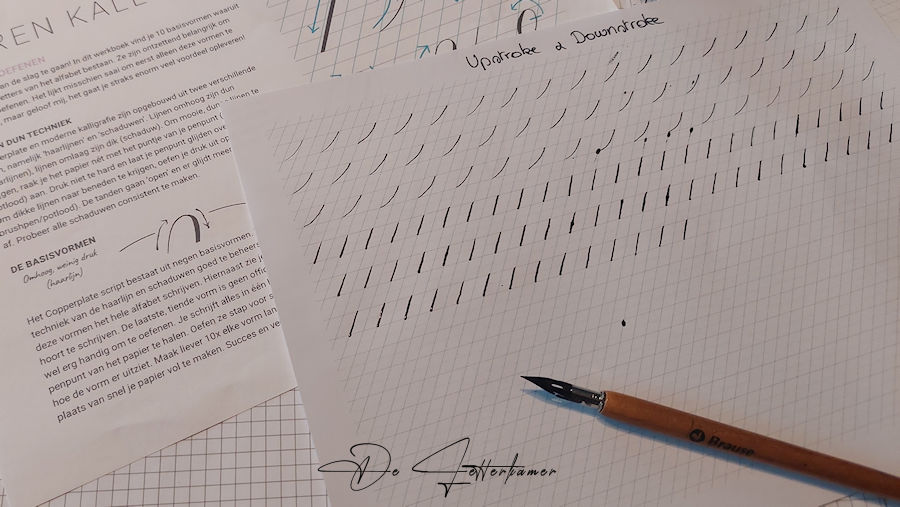
Zo, zoals beloofd de reis gaat verder, en daarover vertel ik meer. Ik ben begonnen met de meeste eenvoudige basisvormen: namelijk de upstroke en de downstroke. De upstroke is meer glijden met de pen over je papier, de downstroke daar zet je meer druk op de pen. De lijnen moeten ook mooi glad zijn ook niet hobbelig. En daar ga ik nog steeds de mist in.
Dit was de 1ste keer en meteen een uitschuiver gemaakt, vlekken gemaakt.
Dit was uiteraard niet de bedoeling, ik heb dan verder gedaan, het stoorde me wel, … ik print me telkens 4 oefenbladeren uit op printpapier Clairefontaine DCP 90g. Mooi glad papier om te oefenen. Elke avond, in de week oefen ik een beetje. Uren aan een stuk is niet voor mij weg gelegd. Je voelt het na een tijdje aan je hand. Het begint krampachtig te worden, of de lijnen en bogen zijn niet zoals het hoort.
Morgen doe ik verder met de andere basisvormen met de rechte pen, en nib Nikko G. Tot nu toe heel tevreden met mijn aankoop